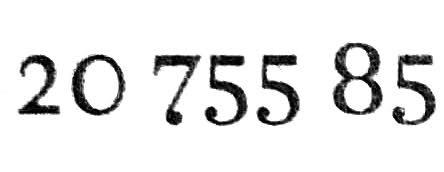
Punze bei 0 verrutscht, 7 mit Tropfen
Welche Schriften haben denn diesen Tropfen unten an der OSF 7 ?
Oder weiß jemand genau diese Schrift, die Strichstärke bei der Null ist links so viel stärker, dass man meint die Punze sei verrutscht …
Hallo, kommt schon ziemlich gut hin.
Die Regent hat Serifen (siehe 2, 5, 7), die an meinem Beispiel nicht dran sind. Die Horizontalen enden ohne Serifen, ähnlich der Georgia Ziffern.
Die Null ist schon mal super.
Die 2 hat auch einen Tropfen.
Und die ganzen kleinen Serifchen …
Wo kommt denn das Beispiel her? Scheint mir mit Blei gedruckt zu sein. Dann ist eher unwahrscheinlich, genau diesen Schnitt digital zu finden.
Das Beispiel kommt von meiner Handy-Kamera. Die Lettern sind so ausgefranst, weil ich den Kontrast für What the font so stark erhöht hab.
Ist sicher eine digitalisierte Schrift. Ich bin schon tausende Male drüber gestolpert.
Irgendwas in die Emigre Richtung – Filosofia – Vendetta – Matrix Script – Mrs Eaves … ich komm nicht drauf.